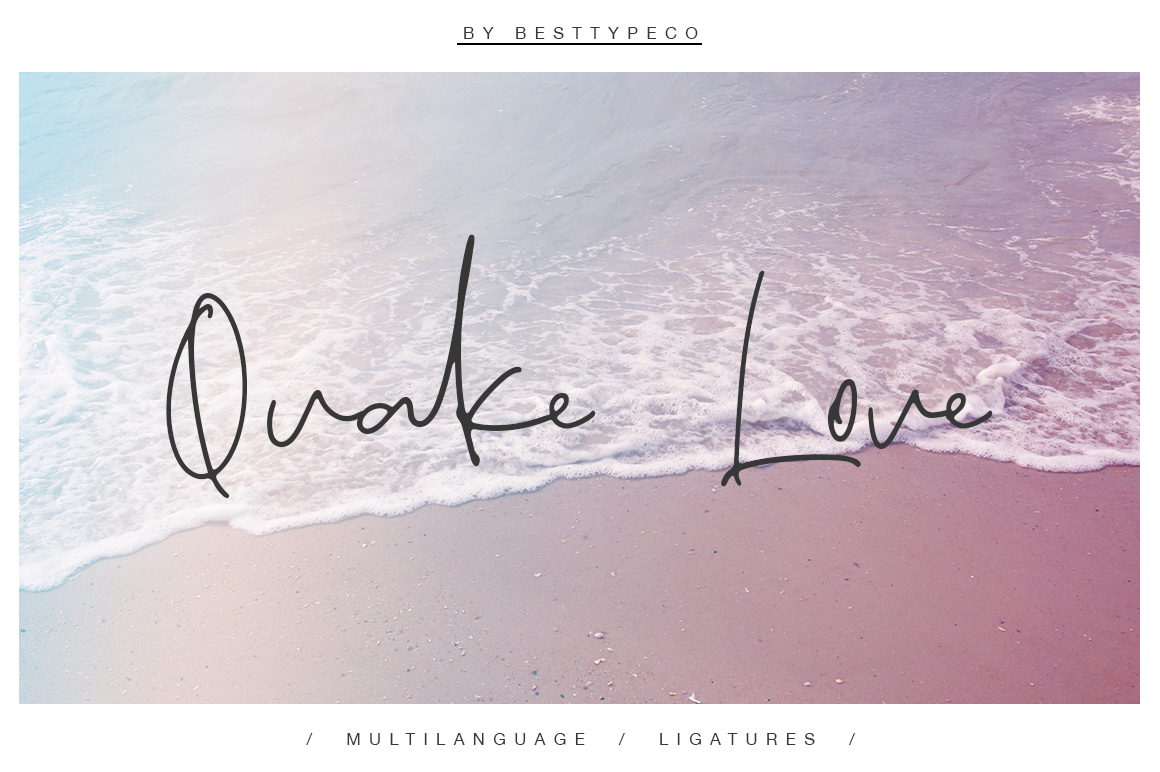
Quake Love Script Font – Download Grátis
A Quake Love Script Font é uma nova fonte escrita à mão, projetada por Alexander para aqueles que buscam uma aparição autêntica e criativa. Perfeita tanto para criações casuais quanto profissionais, esta fonte de letras feitas à mão encaixa-se perfeitamente em um amplo espectro de aplicativos, incluindo cartões de agradecimento, materiais de marca, cartões de negócios, mensagens de resumo, outdoors e muito mais. Além disso, é uma escolha ideal para criar cartões postais de casamento com um toque especial ou pode ser usada para dar um toque único ao logotipo da sua empresa, blog, material de rotulagem, marketing, revistas e outros projetos. Seja a criar algo tradicional ou algo que seja completamente único, a Quake Love Script Font oferece uma aparição autêntica que certamente deixará seu design em evidência.